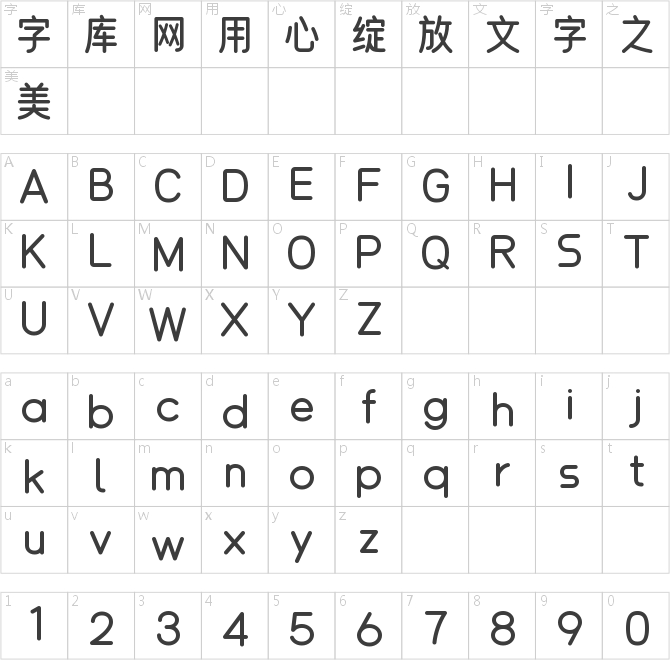
優(yōu)設(shè)鯊魚菲特健康體 詳情頁
由字繪中國發(fā)起,新零售健康輕食品牌鯊魚菲特聯(lián)合優(yōu)設(shè)與字由,為廣大設(shè)計師特推出了一款專為健康而生,電商應(yīng)用場景極強(qiáng)的優(yōu)質(zhì)字體——優(yōu)設(shè)鯊魚菲特健康體。
優(yōu)設(shè)鯊魚菲特健康體字體字庫是一款讓人賞心悅目、百看不厭的中文字體,適合各類廣告和產(chǎn)品包裝設(shè)計應(yīng)用,字體大小3.13MB,格式為ttf字體,上傳用戶是/zyj【GF】,作者/版權(quán)方為優(yōu)設(shè)